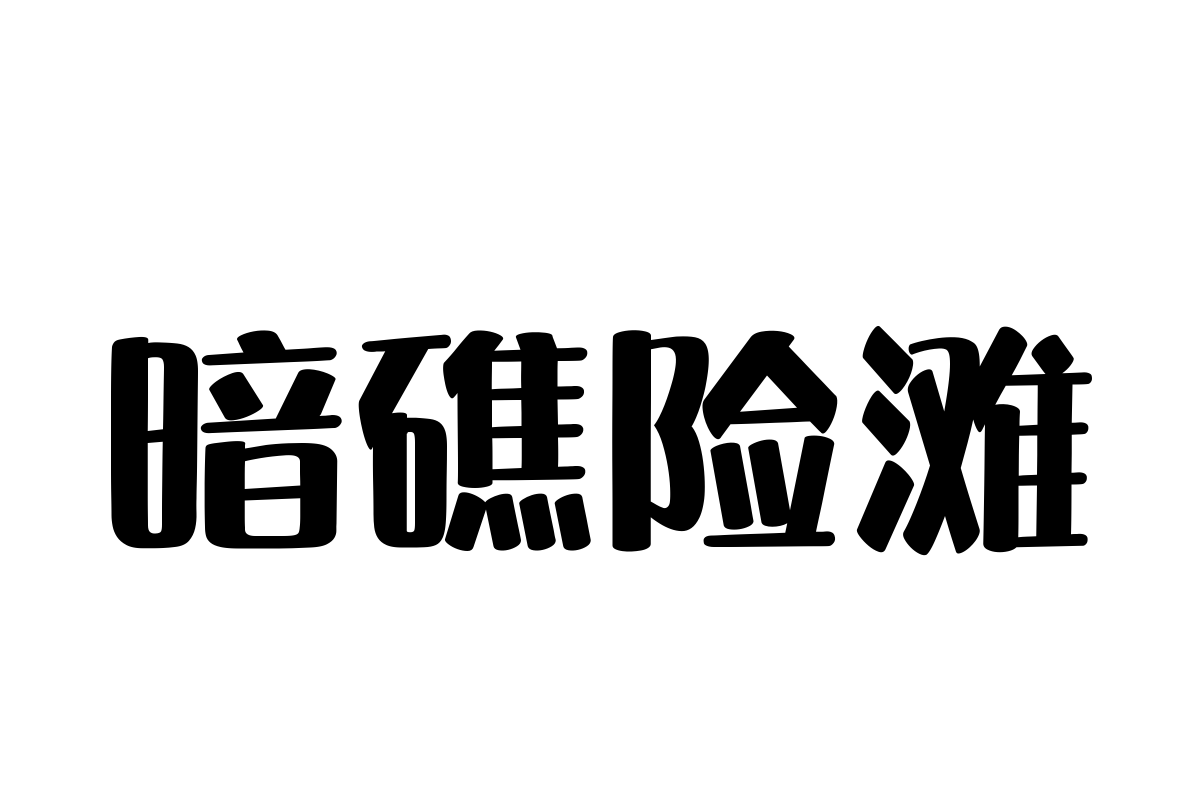
汉仪晓波梦想家是一款具有现代感和艺术气息的中文字体,适用于各种设计项目。这款字体的特点包括:
1. 简洁流畅:汉仪晓波梦想家字体线条流畅,字形简洁,给人一种轻松愉悦的感觉。
2. 艺术性强:这款字体具有很强的艺术性,适合用于需要强调个性和创意的设计项目中。
3. 可读性强:虽然这款字体线条流畅,但字形清晰,易于阅读,不会因为过于复杂而影响信息的传递。
4. 适用范围广:无论是用于印刷品、网页设计还是其他视觉设计项目,汉仪晓波梦想家字体都能很好地融入其中,展现出其独特的魅力。
总之,汉仪晓波梦想家是一款非常适合现代设计项目使用的中文字体,无论是在商业还是艺术领域,都能展现出其独特的风格和价值。
汉仪晓波梦想家